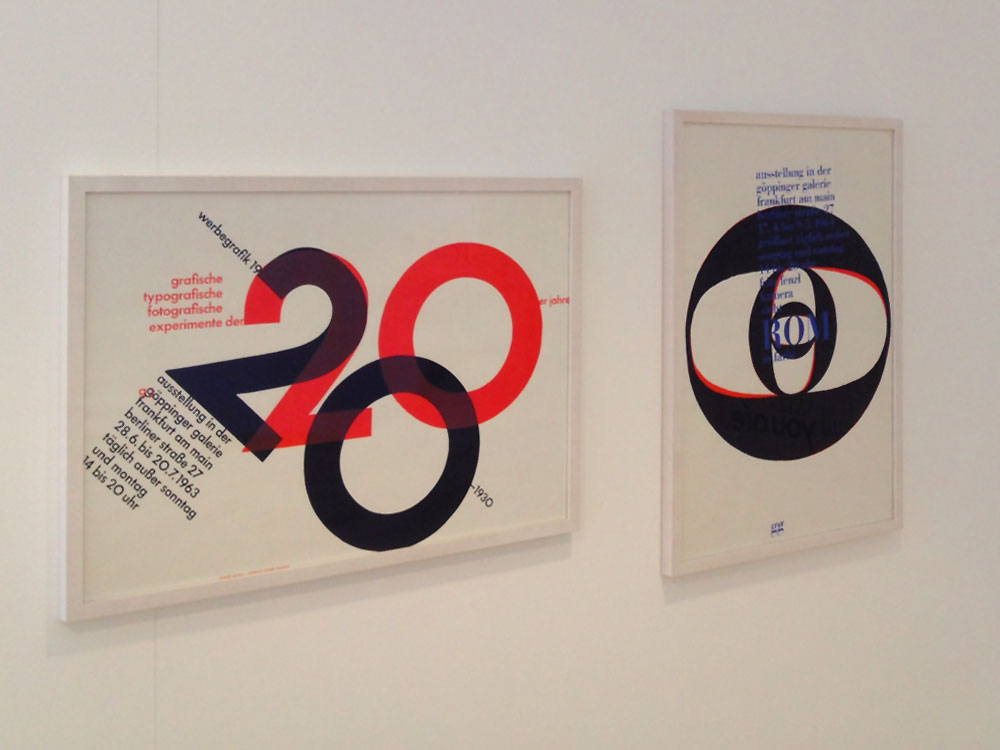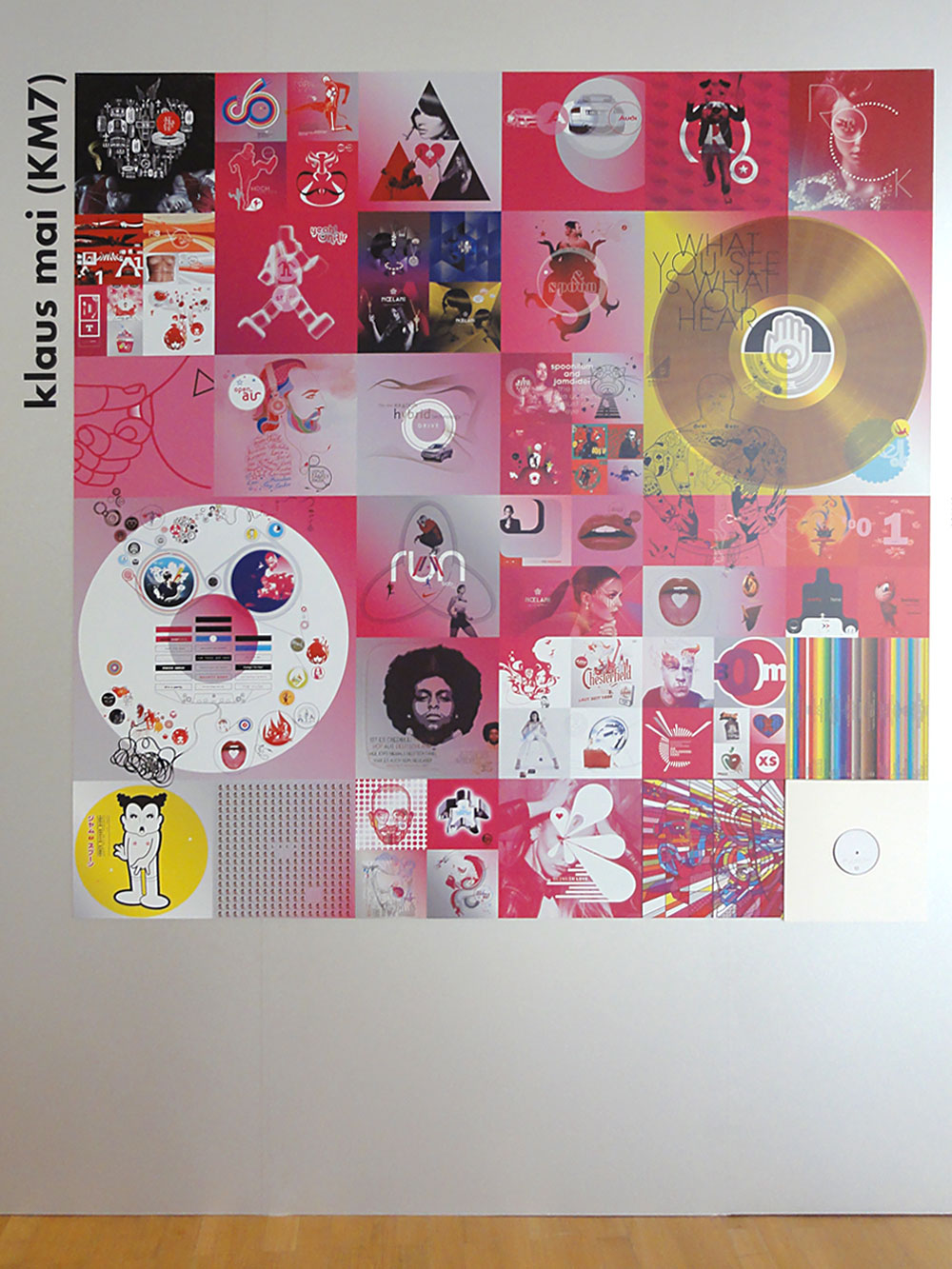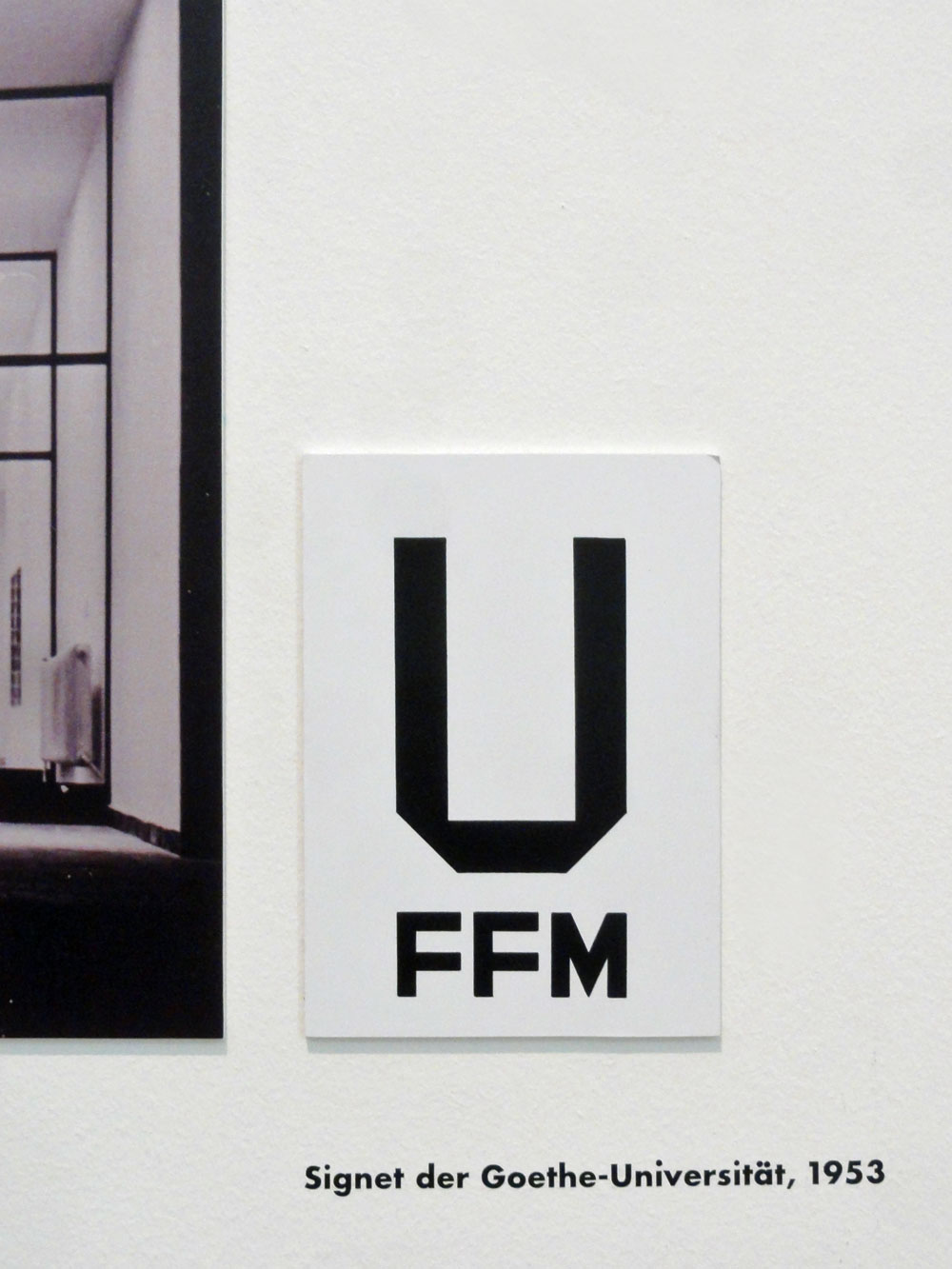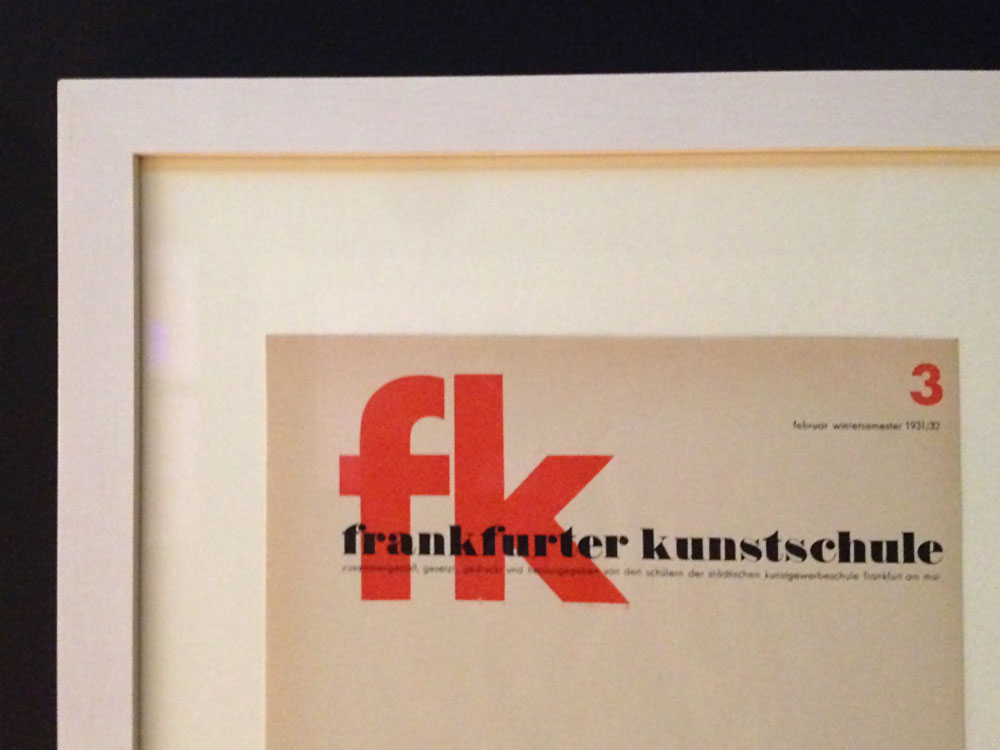
„Das Neue Frankfurt“ war ein Stadtplanungsprogramm nach dem 1. Weltkrieg, welches alle Bereiche der städtischen Gestaltung umfasste. Die damit einhergehenden Aktivitäten im Wohnungsbau gingen in die Architekturgeschichte ein, ebenso stammen Meilensteine der visuellen Gestaltungsmoderne aus Frankfurt.
Was sich seit dieser Zeit in den Bereichen Typografie und Grafikdesign getan hat, ist seit dem 25. März im Museum Angewandte Kunst in Frankfurt zu sehen. Die Ausstellung Alles neu! stellt zwar die 1920er Jahre in den Mittelpunkt, spannt aber den Bogen bis in die heutige Zeit (z.B. KM7, der u.a. Flyer für das XS und den Tunnelrave, sowie Plattencover für Jam & Spoon, Sven Väth, Yello und Tokyo Ghetto Pussy gestaltete) und nimmt somit erstmalig eine systematische Aufarbeitung dieser Epoche für den Bereich Typografie und Grafikdesign vor.
Anbei einige Fotos aus der Ausstellung, die noch bis zum 14. August 2016 läuft.
100 Jahre Neue Typografie und Neue Grafik in Frankfurt - Ausstellung im Museum Angewandte Kunst Frankfurt
Klaus Mai (m7) - 100 Jahre Neue Typografie und Neue Grafik in Frankfurt - Ausstellung im Museum Angewandte Kunst Frankfurt
Frankfurter Sportgemeinde Eintracht - 100 Jahre Neue Typografie und Neue Grafik in Frankfurt - Ausstellung im Museum Angewandte Kunst Frankfurt
100 Jahre Neue Typografie und Neue Grafik in Frankfurt - Ausstellung im Museum Angewandte Kunst Frankfurt
Frankfurter Schule - 100 Jahre Neue Typografie und Neue Grafik in Frankfurt - Ausstellung im Museum Angewandte Kunst Frankfurt
Signet der Goethe Universität - 100 Jahre Neue Typografie und Neue Grafik in Frankfurt - Ausstellung im Museum Angewandte Kunst Frankfurt
Frankfurter Kunstschule - 100 Jahre Neue Typografie und Neue Grafik in Frankfurt - Ausstellung im Museum Angewandte Kunst Frankfurt
100 Jahre Neue Typografie und Neue Grafik in Frankfurt - Ausstellung im Museum Angewandte Kunst Frankfurt